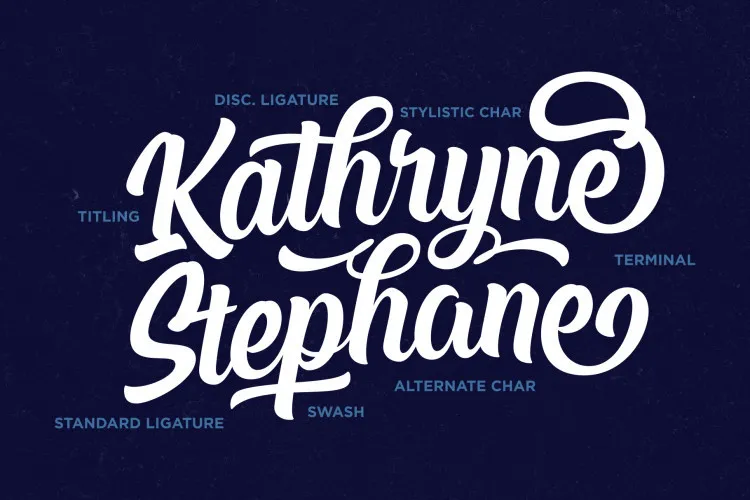
Chuck Noon Script Font – Fonte Grátis
Chuck Noon Script Font
Olá! Estou aqui a melhor tipografia no gosto script. Hoje introduzimos Chuck Noon para você. Foi criado pela Twicolabs Fontdation e é uma fonte de script limpa e ousada que oferece uma experiência natural de escrita à mão. O design foi cuidadosamente elaborado e verificado digitalmente, com foco em linhas limpas e bordas críticas. É um tipo de letra dinâmico que se move como mágica: funciona tanto ao usar apenas letras maiúsculas quanto ao usá-la normalmente como fonte script. E o melhor de tudo é que se adequa perfeitamente a logotipos, designs para posters e camisetas, rótulos para alimentos/bebidas, cartões de felicitações, convites de casamento – praticamente para qualquer aplicação criativa. A Twicolabs Fontdation tem um compromisso constante em criar tipos de letra que refletem as nossas preferências e estilos únicos. Então, se você também valoriza linhas retas e bordas finas, certamente vai adorar Chuck Noon!
Designer: Daikian